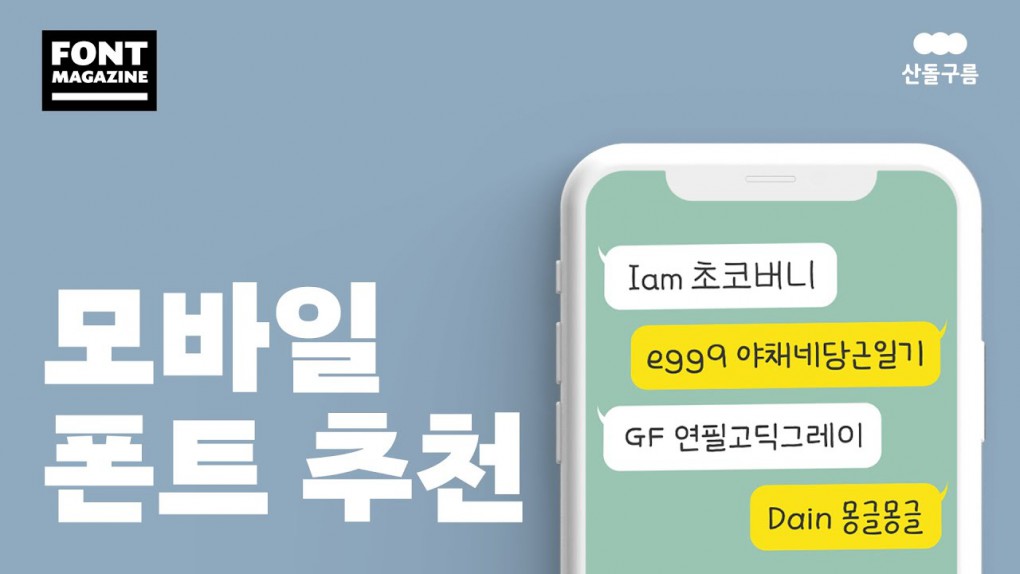
모바일 인기 폰트 TOP3 딱 정해 드립니다!
‘폰꾸 너무 좋아! 내 폰을 더 예쁘고 귀엽게 만들고 싶어😍’ 라는 마음을 가진 분,
‘모바일 폰트 너무 많아.. 내 폰에 딱 맞는 폰트.. 그냥 누가 딱 정해줬으면 좋겠다..’ 라는 마음을 가진 분,
모두 주목해 주세요! 산돌구름이 추천하는 모바일 폰트 TOP3 추천 들어갑니다.💙
산돌구름이 추천하는 모바일 인기 폰트 3위는, 모바일 폰트의 최강자 중 하나인 ‘Dain 몽글몽글’ 입니다.
이름처럼 둥글둥글 발랄한 폰트이고, 속공간이 깔끔하게 정리되어 있어 가독성이 좋은 것이 인기의 비결로 보이네요.
다음, 모바일 인기폰트 2위는 ‘Cat 월화수목금토일’ 입니다. 디자이너피셜 ‘0.5mm 펜으로 쓴 생기발랄한 손글씨’ 라는 느낌을
잘 표현 해 주는데요, 초성-중성의 이음새가 좌우 랜덤하게 제작되어 재미를 선사하는 폰트네요😉
모바일 인기 폰트 TOP 3 외에도, 귀엽고 안 질리는 모바일 폰트 추천과 실제 적용 방법까지 상세히 소개 해 드리니,
이번에는 까만 토끼의 해, 계묘년에 딱 맞는 모바일 폰트인 ‘Iam 초코버니’와 함께 쓰면 귀여움이 2023배가 되는 테마를 준비했어요.